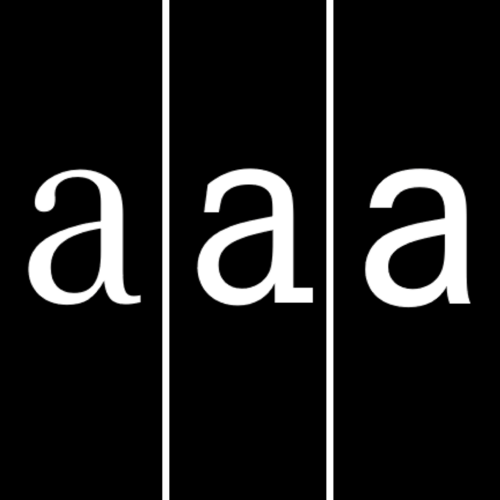
Die Compatil ist eine 2001 erschienene Schriftsippe, die vier Schriftstile zusammenfasst. Ausgangspunkt waren komplexe gestalterische Aufgaben wie die Gestaltung von Jahresberichten von Kapitalgesellschaften. Die Sippenmitglieder sind jeweils in vier Schnitten mit 387 Glyphen ausgebaut. Als Besonderheit sind die Dickten der Buchstaben über alle vier Familien identisch, so dass sich die zugehörigen Schriften miteinander austauschen lassen, ohne dass sich der Umbruch ändert.
Compatil
von
Olaf Leu
Silja Bilz
Compatil Exquisit
Compatil Text
Compatil Fact
Compatil Letter